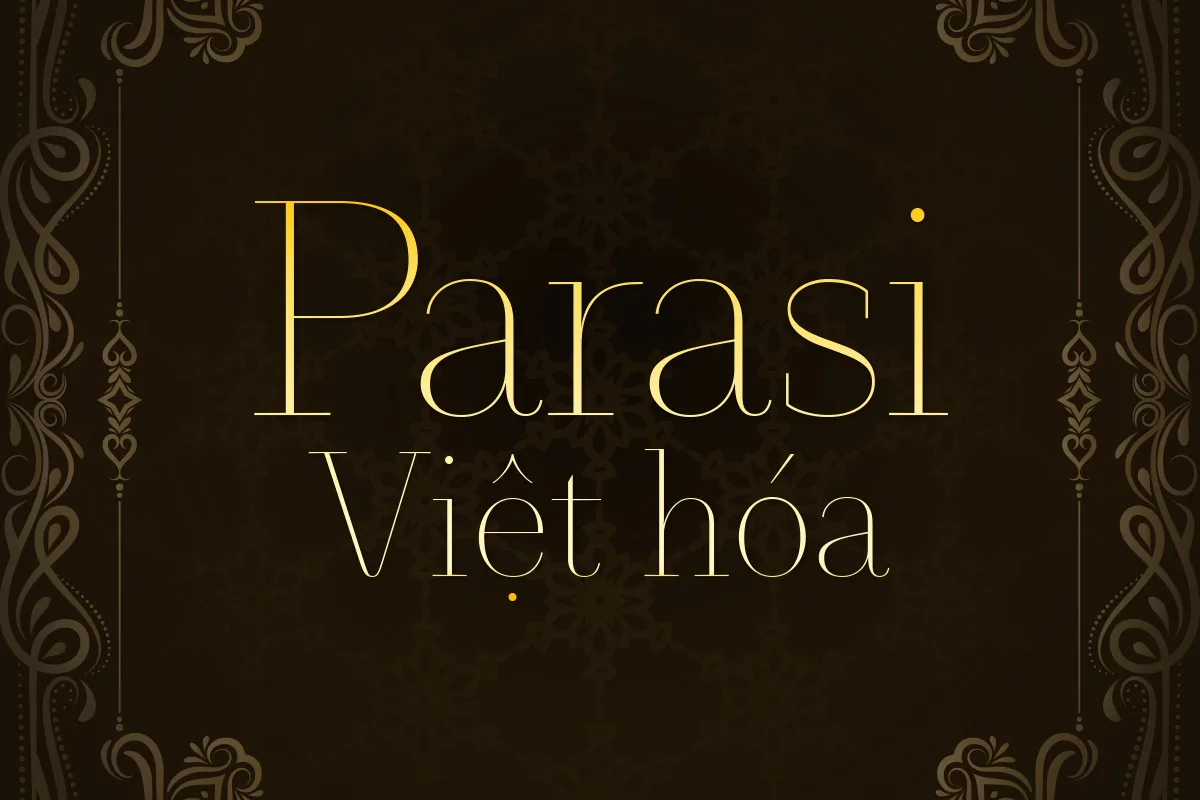
DVN Parasi Việt hóa- Font chữ thanh lịch cho mọi thiết kế
Font Parasi Việt hóa mang phong cách thanh lịch, tinh tế và hiện đại, được thiết kế với những đường nét mảnh mai, thanh thoát nhưng vẫn giữ được sự vững vàng trong bố cục chữ.
Đặc điểm nổi bật:
Kiểu dáng serif cao cấp: Các nét mảnh – đậm được phối hợp nhịp nhàng, tạo cảm giác sang trọng và dễ đọc.
Cân đối hài hòa: Khoảng cách giữa các ký tự được xử lý cẩn thận, phù hợp cho cả văn bản ngắn và tiêu đề dài.
Việt hóa đầy đủ: Hỗ trợ trọn bộ dấu tiếng Việt, đảm bảo sử dụng linh hoạt trong thiết kế nội dung bản địa.
Phong cách cổ điển pha hiện đại: Giữ nét trang nhã, phù hợp từ các thiết kế cao cấp như bao bì, thương hiệu thời trang, mỹ phẩm, nhà hàng – khách sạn, cho đến thiệp mời, poster hay sách báo.